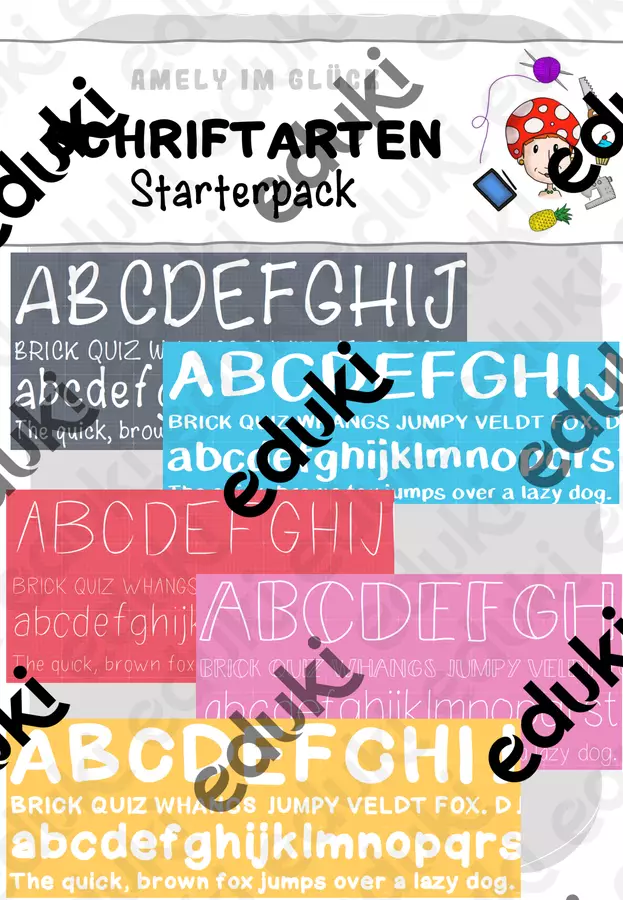
Ich bin ein Schriftartenjunkie! Du auch? Dann kannst du mit diesem Schriftartenpaket 5 weitere Schriftarten in deiner Sammlung willkommen heißen! Von auffällig dick bis einfach und unauffällig ist einiges dabei!
Schriftarten Starterpack "von dick bis dünn"